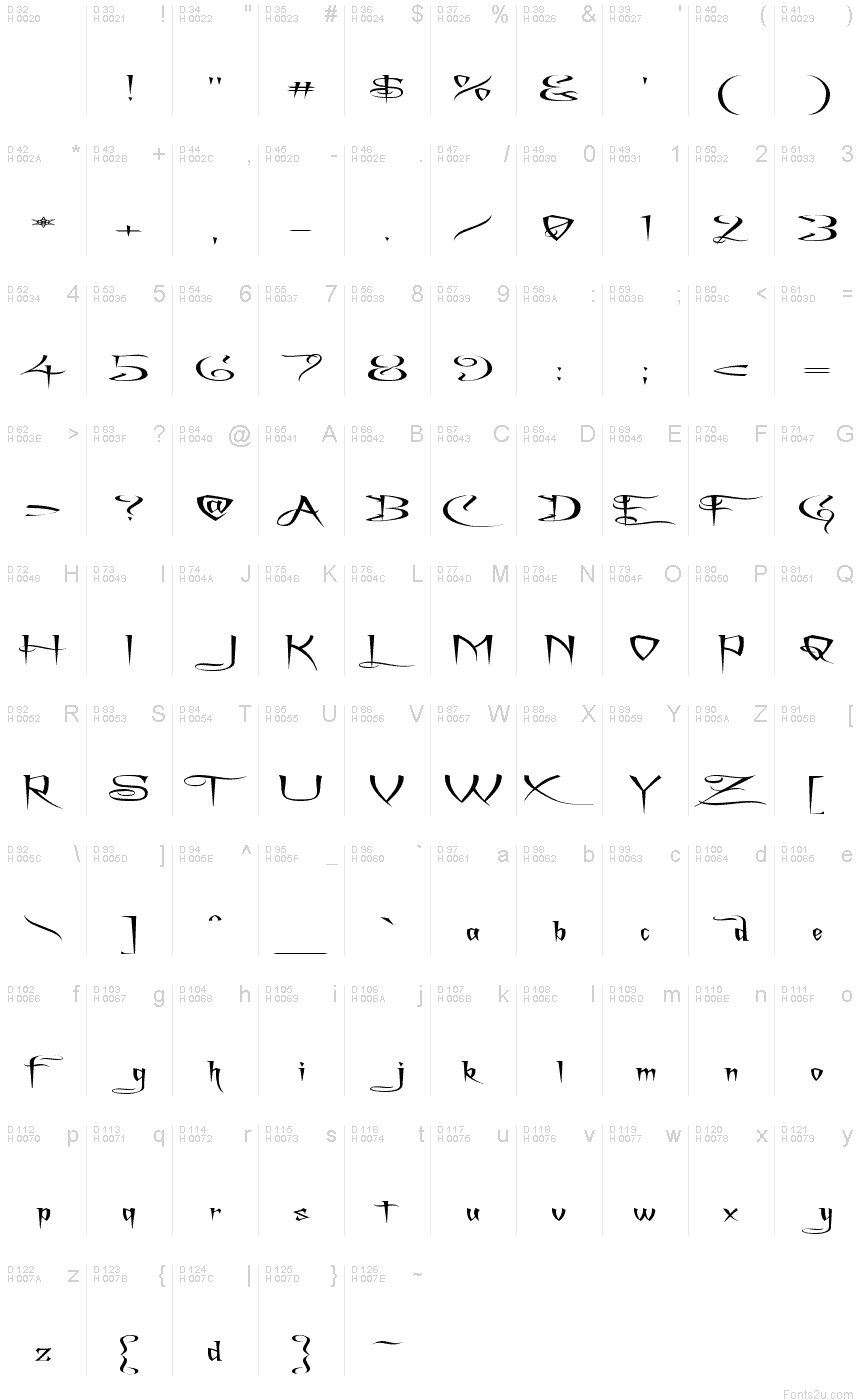
A Charming Font Superexpanded
A Charming Font Superexpanded di GeM / A. Höfeld è un carattere display gotico gratuito che rielabora il dramma della classica blackletter in una veste più ampia e teatrale. I tratti sembrano disegnati a mano e intrisi d'inchiostro, con curve sinuose e bordi pungenti che richiamano scritte tracciate su pergamena a lume di candela. Grazie alla larghezza estesa, le lettere hanno più respiro rispetto alle tipiche grafiche gotiche, offrendoti quell'aura medievale misteriosa senza compromettere la leggibilità in titoli o loghi.
Utilizzando A Charming Font Superexpanded, parte della famiglia A Charming Font, puoi definire all'istante il tono di copertine fantasy, titoli di giochi RPG, loghi di band gothic, locandine di eventi, branding a tema tarocchi o occulto, o miniature YouTube di grande impatto. Questo font gratuito brilla nelle dimensioni più grandi, dove i suoi ghirigori possono espandersi e intrecciarsi. Per mantenere l'equilibrio, abbinalo a un carattere sans serif pulito e neutro per il corpo del testo, così che le forme ornamentali restino le vere protagoniste del tuo layout.